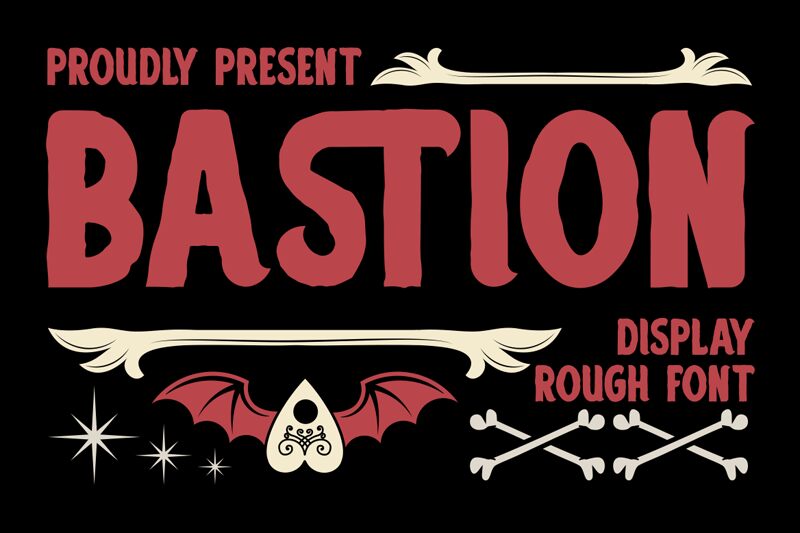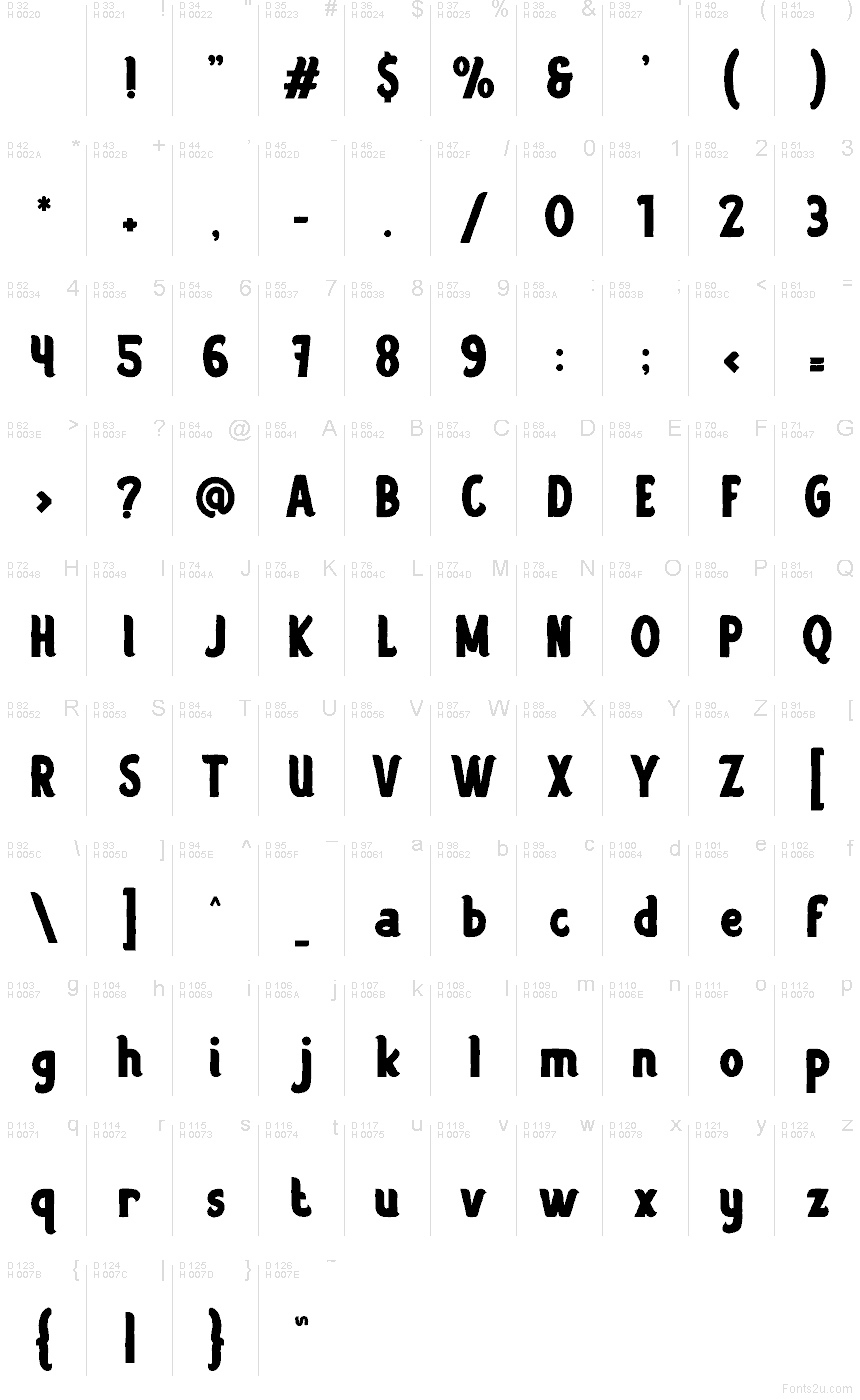
Bastion od Putracetol Studio je bezplatné gotické display písmo s měkkou, masivní siluetou a lehce středověkou atmosférou. Písmena v sobě spojují výraznou váhu se zaoblenými hranami a hlubokými zářezy, takže textura působí spíše robustně a starosvětsky než tvrdě.
Skvěle se hodí na plakáty, branding hospod, názvy her, obaly a titulky, kde trocha historického nádechu pomůže dotvořit celkový dojem. Jako bezplatné písmo funguje Bastion výborně i pro krátká loga a názvy, protože jeho široké, tmavé tvary a hluboké zářezy dodávají i několika málo znakům kompaktní, vytesaný vzhled.